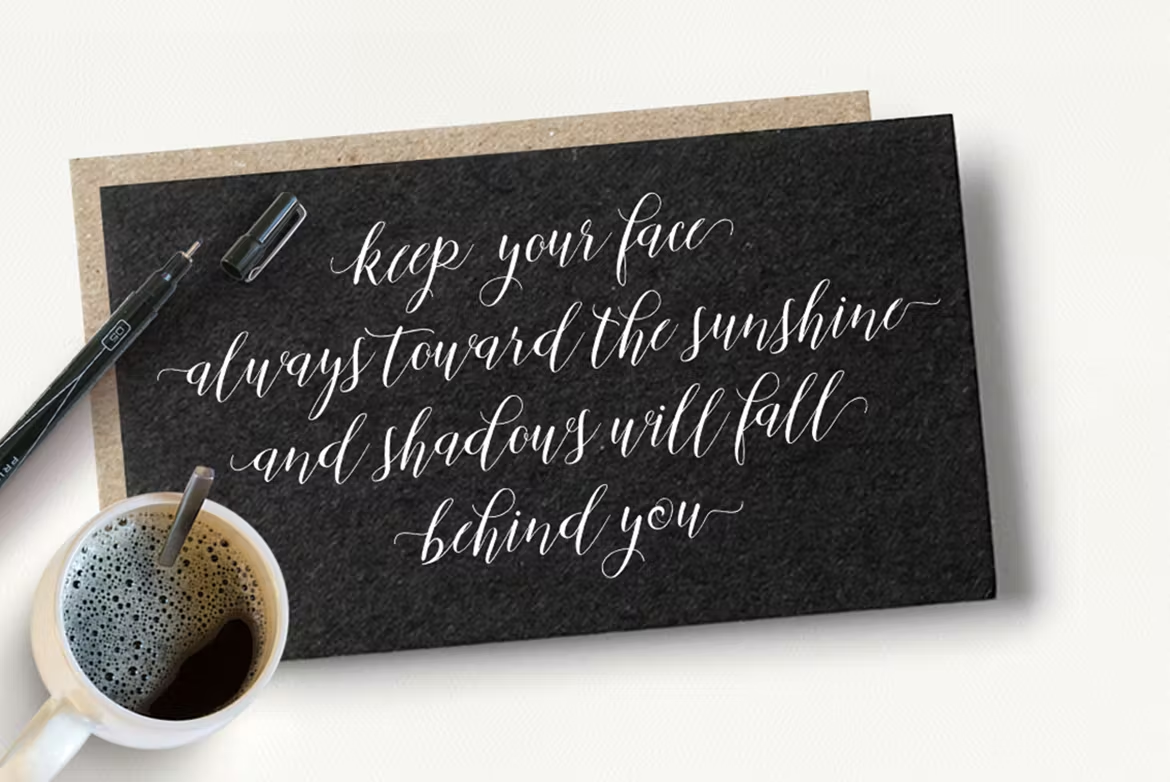
Mallicot Script Font
Description de Mallicot Script Font
Mallicot Script + Extras est un manuscrit calligraphique moderne, dynamique et joli avec des swashes. Peut être utilisé à de nombreuses fins. tels que le titre, la signature, le logo, les invitations de mariage, le papier à en-tête, la signalisation, les étiquettes, les newsletters, les affiches, les badges, etc.